手写的意思是指用手在纸张上的写作方式,这其中包括硬笔手写、毛笔手写等写作方式。手写字体一般极具个人感情色彩,样式多样。
浅夏花开字体是一款可商用的硬笔手写字体,具有女性、现代、优雅、简约的风格,可以满足您设计上的各种需求,该字体主要用于店铺、活动、美食餐饮、健康养生、青春校园 等场景。
璀璨于黑夜是一款可商用的硬笔手写字体,具有温柔、婉约、手写风、简约 的风格,可以满足您设计上的各种需求,该字体主要用于海报企宣、书籍、店铺、活动、健康养生 等场景。
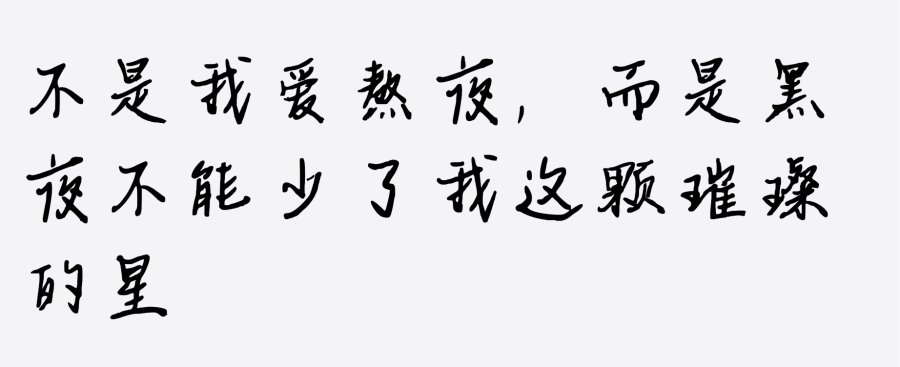
粉色甜系手账字体是一款可商用的硬笔手写字体,具有女性、现代、优雅、简约的风格。